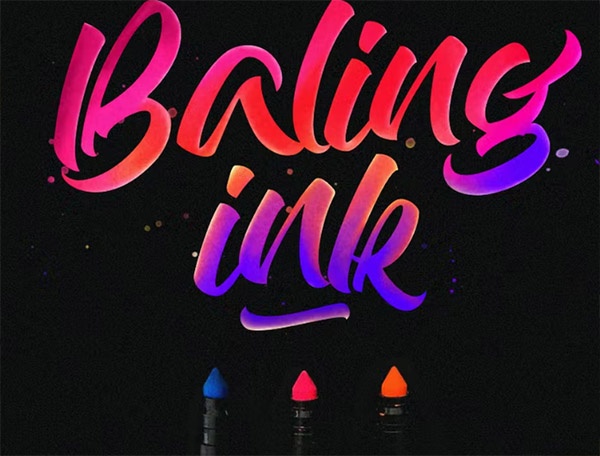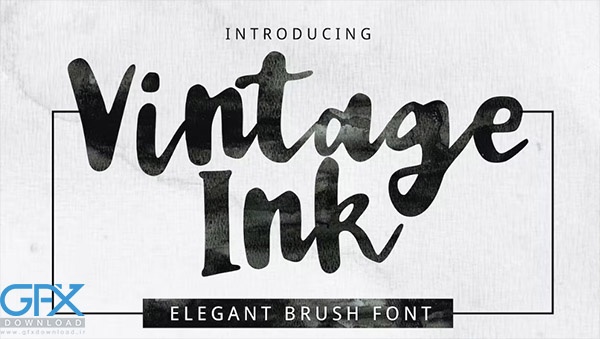
این مجموعه شامل 2 فونت زیبا با قلم مو و طراحی دستی با نام های Baling Ink و Vintage Ink است که به شما کمک میکند ظاهری با حروف دستی سفارشی خیرهکننده ایجاد کنید. دانلود فونت انگلیسی جوهری امکانات ترکیبی متعددی را بین مجموعه حروف اصلی و مجموعه های مدرن ارائه می دهد. با استفاده از برنامه های هوشمند OpenType مانند Adobe به آنها دسترسی پیدا کنید. فونت جوهری چند منظوره ساده، مناسب برای بسیاری از پروژه های کتاب کودکان، نقل قول ها، آرم، عنوان، عنوان و غیره می باشد.